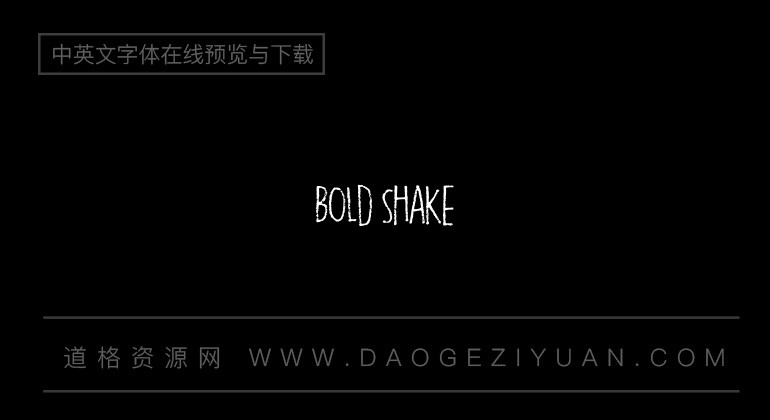
Bold Shake 字体是一种手写风格的字体,其特点是字母和符号的笔画看起来像是用粗笔画的,使得文字具有非常醒目的效果。它是由一个名叫 Misti's Fonts 的设计师制作的。 Bold Shake 字体常用于设计、广告、海报、贺卡、包装等领域,因其独特的手写风格,可以营造出温馨、自然、轻松的氛围,非常适合与一些具有亲和力或者俏皮风格的设计元素搭配使用。 Bold Shake 字体拥有多种字体格式,例如 TrueType、OpenType 和 WebFont,可以在多种设备和平台上使用。此外,它还包含大量的特殊字符和符号,包括多种货币符号、箭头、星星、心形和其他装饰性符号,可以满足各种不同的设计需求。内容介绍
Bold Shake是一款非常不错的手写艺术字体,具有很好的视觉感,适合于文化类的宣传设计、商业类品牌的广告和产品包装设计以及个性化文字排版等较多场景。